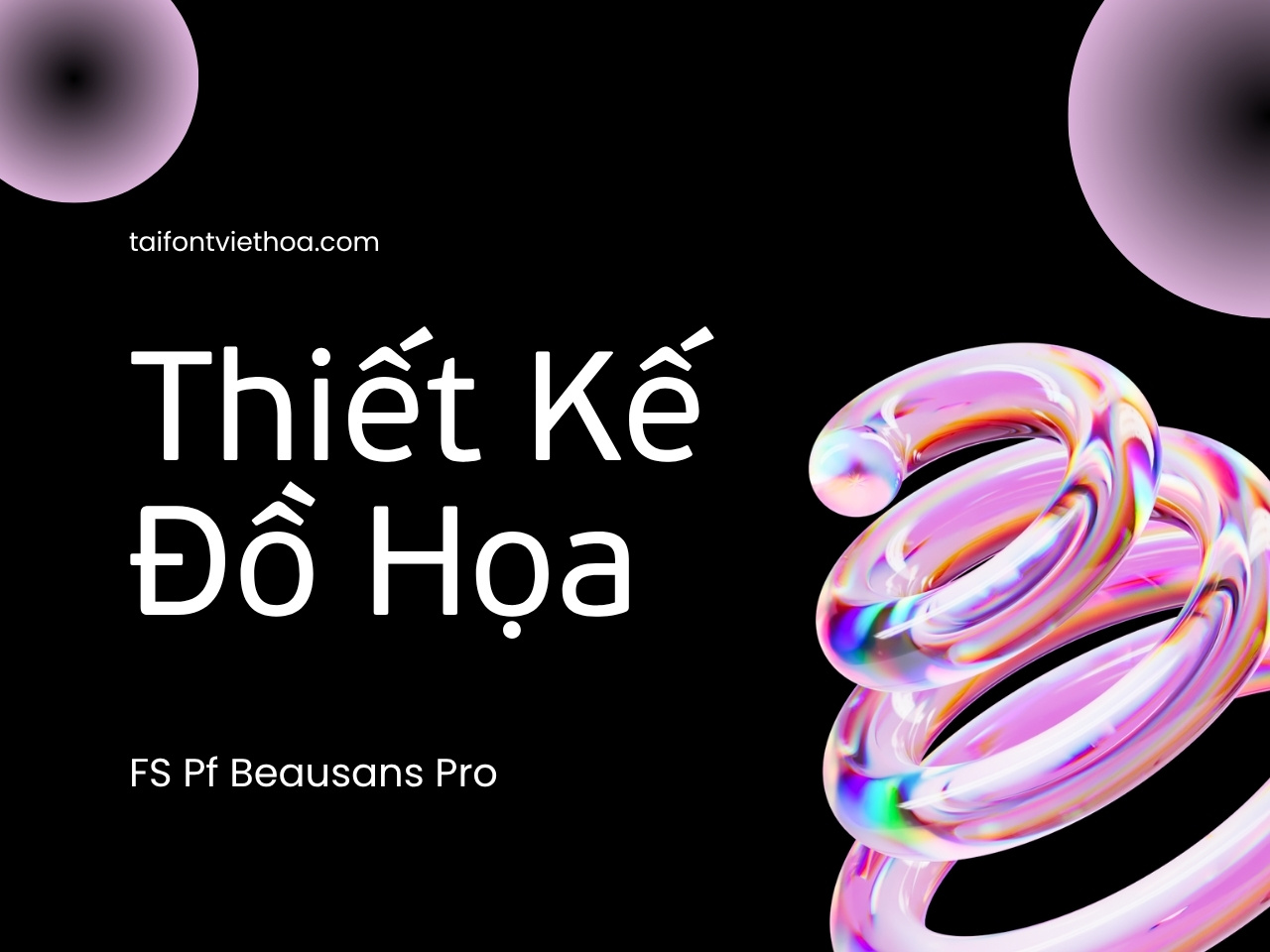
Font việt hóa FS Pf Beausans Pro
Tác giả Font: Panos Vassiliou
Giới thiệu về font PF BeauSans Pro – Phong cách hiện đại, chuẩn quốc tế
PF BeauSans Pro là một kiểu chữ sans-serif hiện đại đến từ hãng thiết kế Parachute – một trong những nhà phát hành font uy tín tại Hy Lạp, nổi tiếng với các bộ font chuyên nghiệp phục vụ lĩnh vực xuất bản và thương hiệu. Font được phát triển bởi Panos Vassiliou, lần đầu ra mắt vào năm 2011 và nhanh chóng trở thành lựa chọn hàng đầu trong các dự án thương mại cao cấp nhờ khả năng tương thích tuyệt vời với nhiều hệ ngôn ngữ và nền tảng thiết kế.
Phiên bản Việt hóa với tên gọi FS PF BeauSans Pro đã được hiệu chỉnh hoàn chỉnh, hỗ trợ đầy đủ tiếng Việt và hơn 90 ngôn ngữ khác dựa trên bảng mã Latin mở rộng. Với độ chính xác cao trong việc tái hiện cấu trúc gốc, bản Việt hóa giữ nguyên tính hiện đại, rõ ràng và hiệu quả thị giác của font. Font này được taifontviethoa.com chọn lọc, sưu tầm, kiểm tra và chia sẻ lại nhằm phục vụ các nhà thiết kế, thương hiệu và doanh nghiệp tại Việt Nam trong việc nâng cao chuẩn mực thẩm mỹ và khả năng nhận diện thương hiệu.
Đặc trưng thiết kế tinh giản và khả năng ứng dụng rộng của FS PF BeauSans Pro
FS PF BeauSans Pro mang đặc điểm của một hệ thống font sans-serif đa năng với các đường nét gọn gàng, tỉ lệ cân đối, chiều cao chữ ổn định và khoảng cách giữa các glyphs hợp lý. Với hơn 18 trọng lượng (weights) từ Hairline đến Black cùng nhiều biến thể nghiêng (italic), font cho phép người dùng linh hoạt trong việc phân cấp thông tin và tạo điểm nhấn trực quan.
Font phù hợp để sử dụng trong thiết kế giao diện số (UI/UX), sách, tạp chí, hồ sơ doanh nghiệp (corporate identity), bản tin, tài liệu marketing, cũng như hệ thống nhận diện thương hiệu chuyên nghiệp. Với tone thiết kế trung tính, hiện đại, FS PF BeauSans Pro rất thích hợp cho các ngành như công nghệ, tài chính, giáo dục, y tế và cả quảng cáo số. Đây cũng là lựa chọn lý tưởng trong các chiến dịch truyền thông đòi hỏi tính trang trọng và rõ ràng về mặt ngôn ngữ.